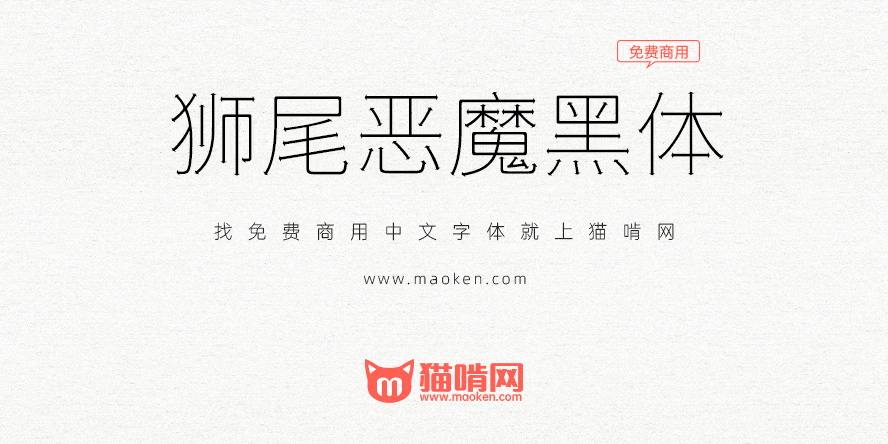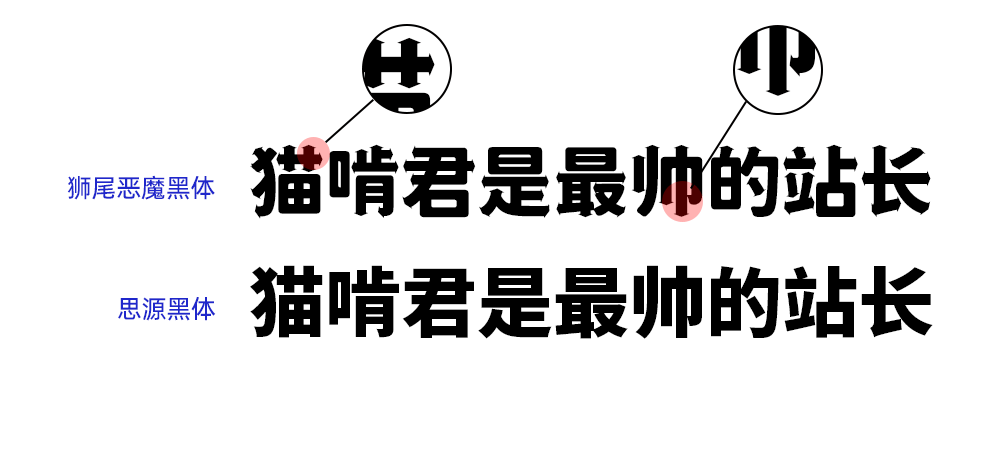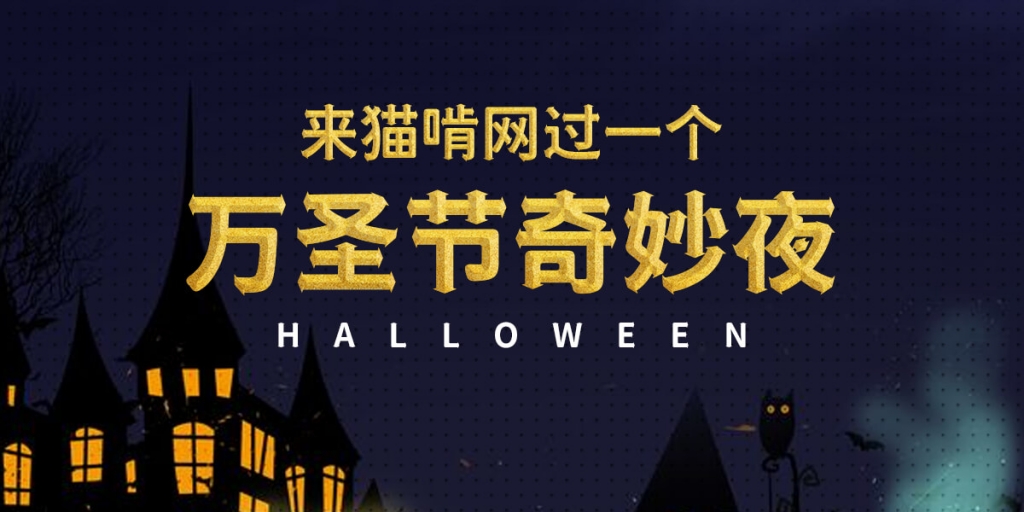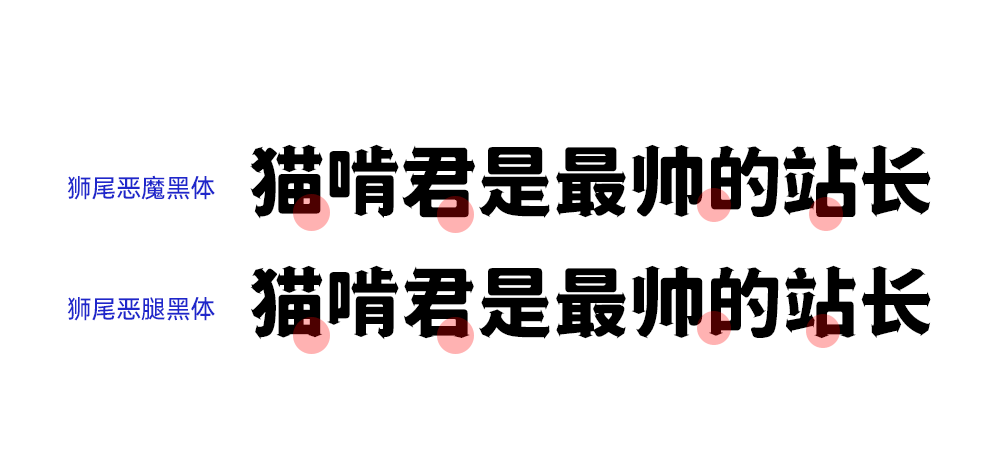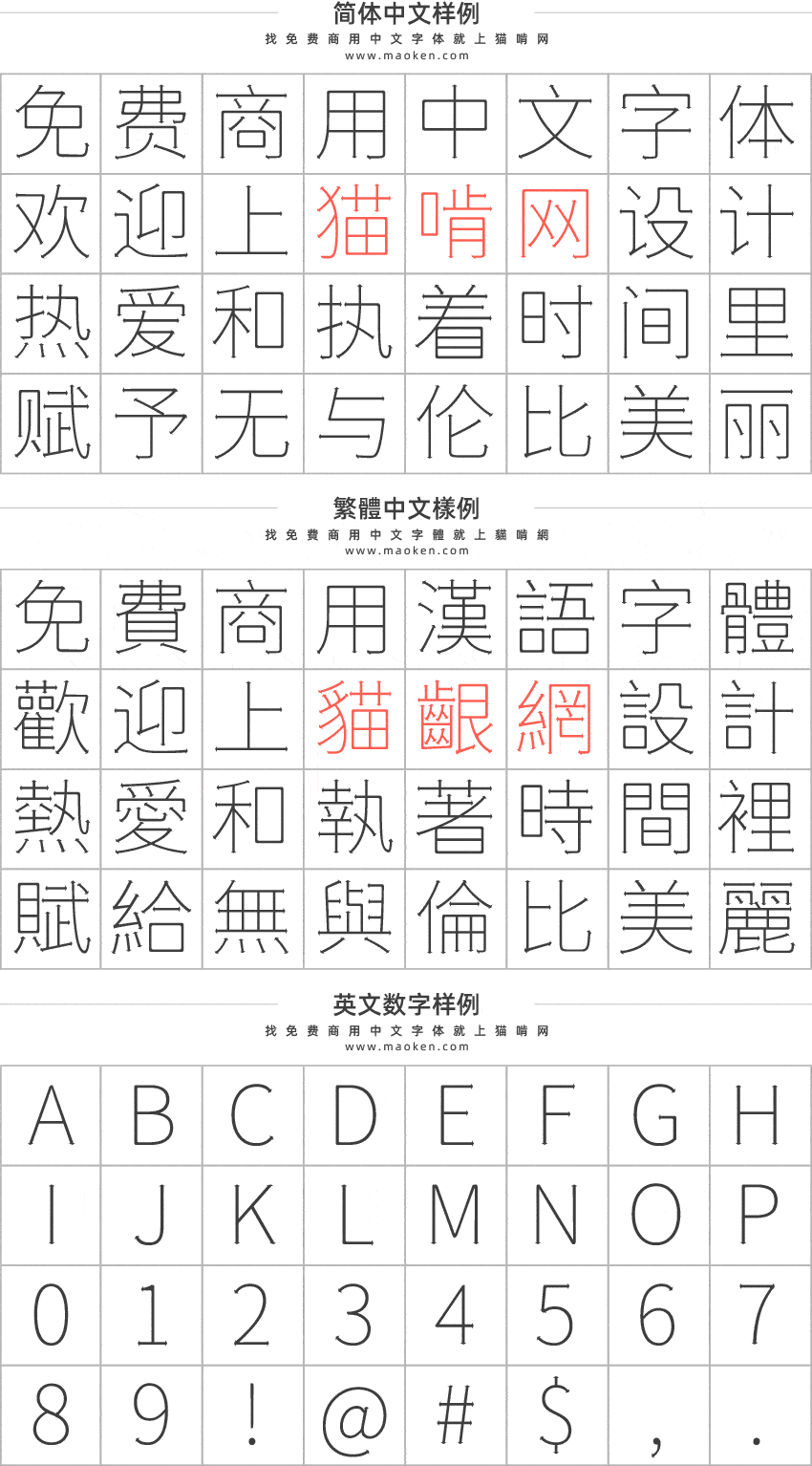
狮尾恶魔黑体基于思源黑体增加三角箭头衬线改造,更加简明现代化的字体。狮尾恶魔黑体的特色是笔触起头与收尾有三角形箭头。这款字体增加了三角形箭头之后,给字体增添一份神秘的感觉。比较适合一些类似万圣节,圣诞节等节目气氛的设计。下面是狮尾恶魔黑体与思源思体的对比效果图。
下面是猫啃君用这款字体做了一个简单的海报示例,感觉这款字体的气质还是能拿捏得死死的。
Max发布的字体一般包括两个版本,就是恶魔黑体和恶腿黑体。这两款字体的最主要区别是有脚和没有脚的区别。有拔脚的字会较圆,但是会造成有些字因直接去掉腿后左右不平衡、左右不对衬的「悬空」问题。改使用「腿」系列字体就不会有这个问题。